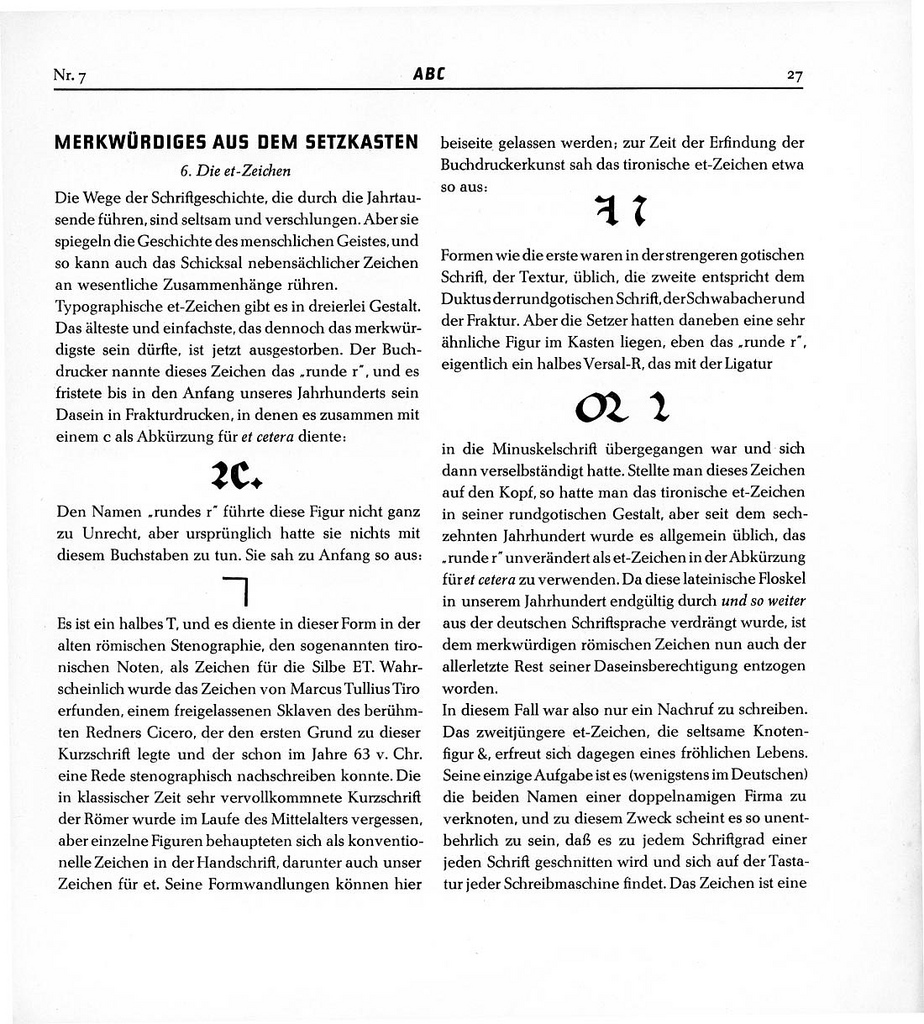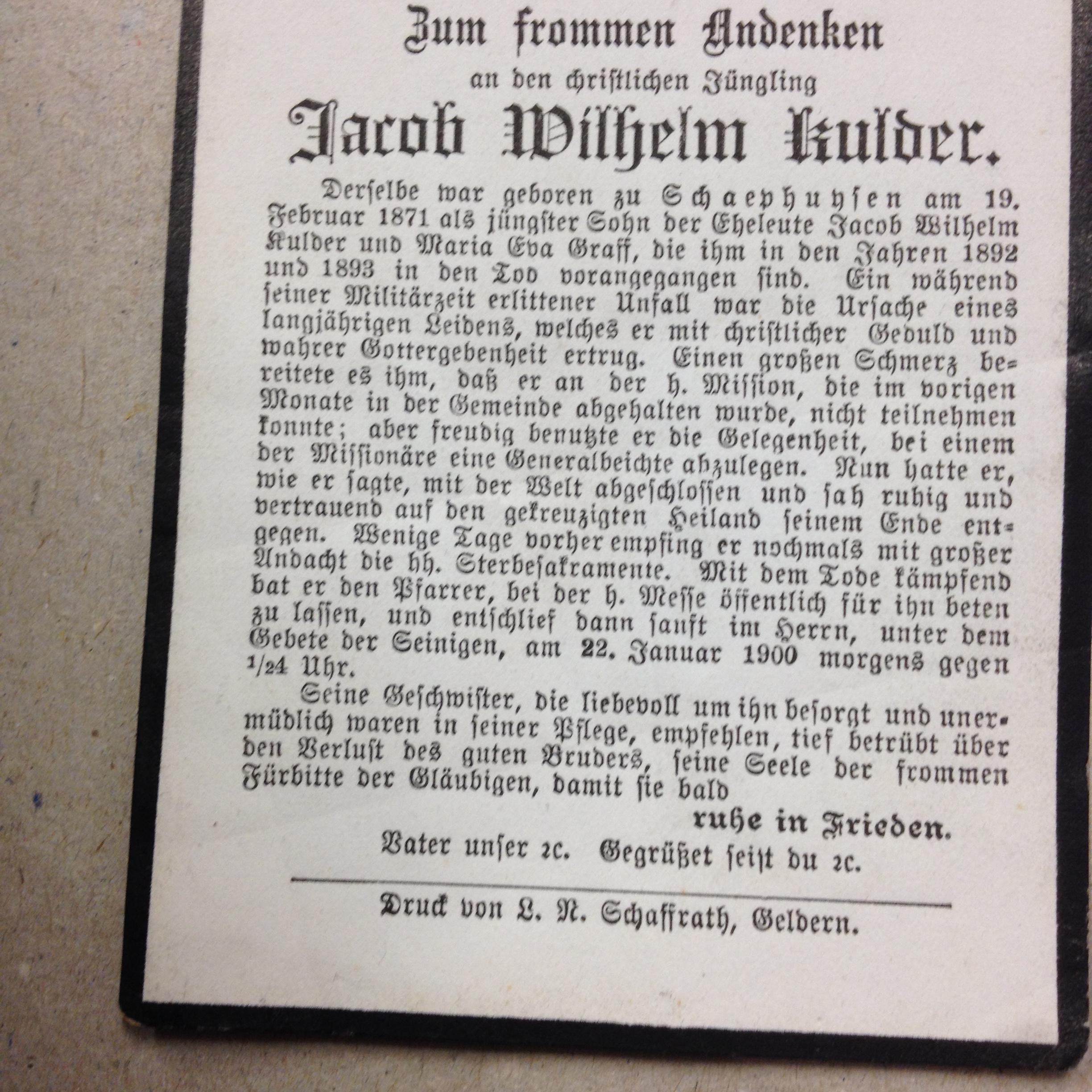
mein Druckerkollege Fritz hat diese alte Dodesanzeige mitgebracht und es entbrannte zwischen uns eine heftige Debatte, ob denn nun neben "Vater unser" und "Gegrüßet seist Du" ein "etc." steht – oder doch eine Aufforderung, dies "2 x" zu beten?
Ich war fest davon überzeugt, dass es KEIN etc. ist.